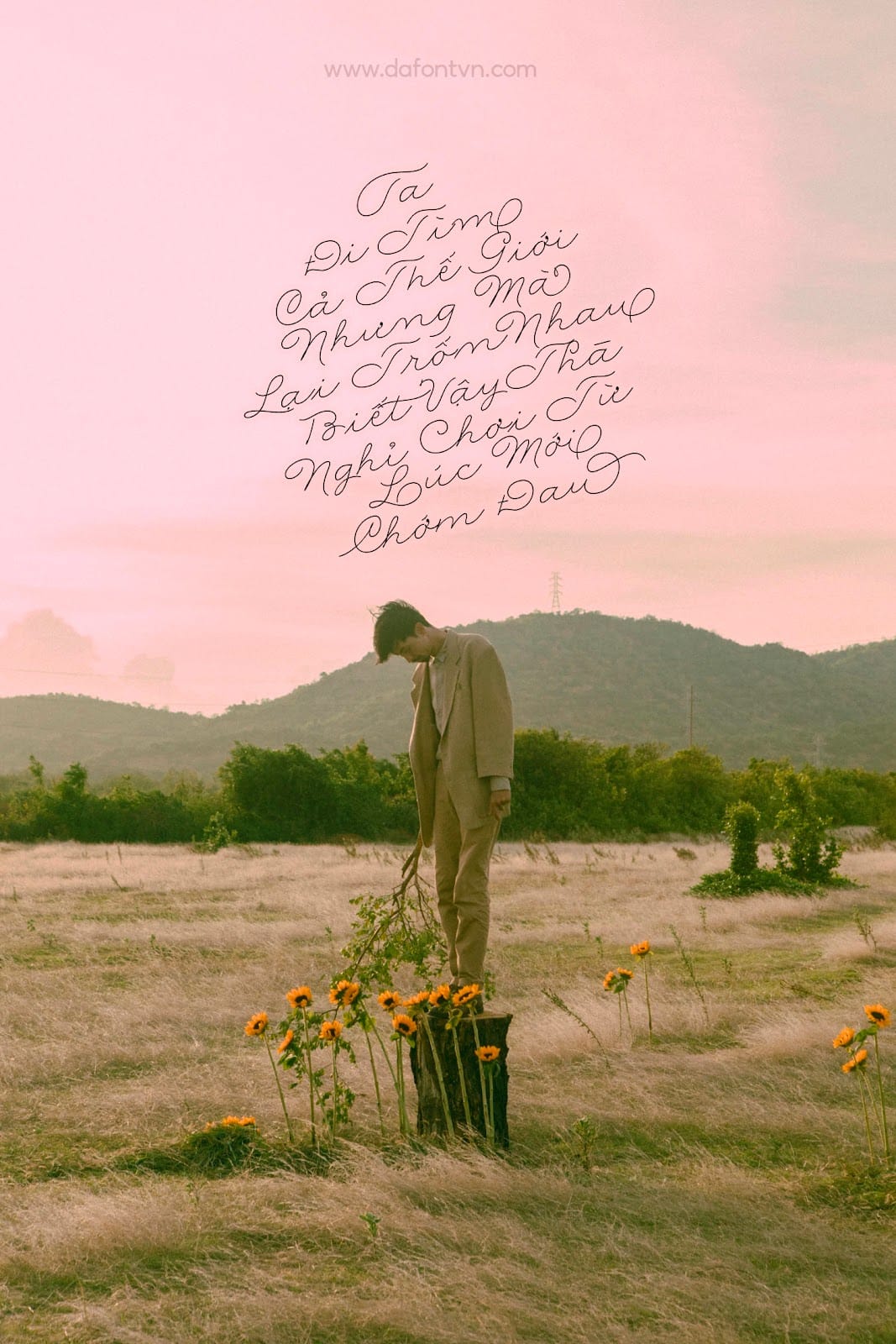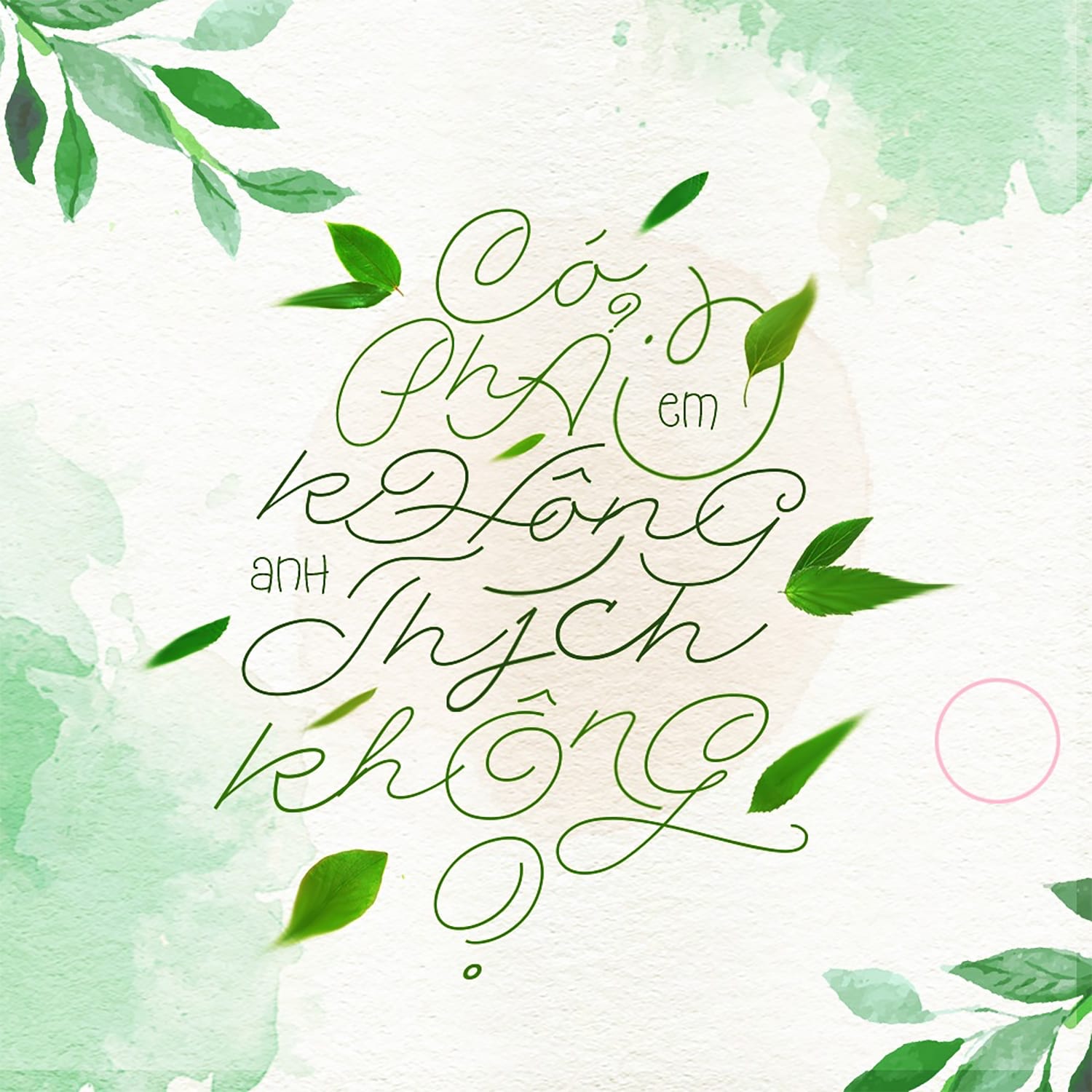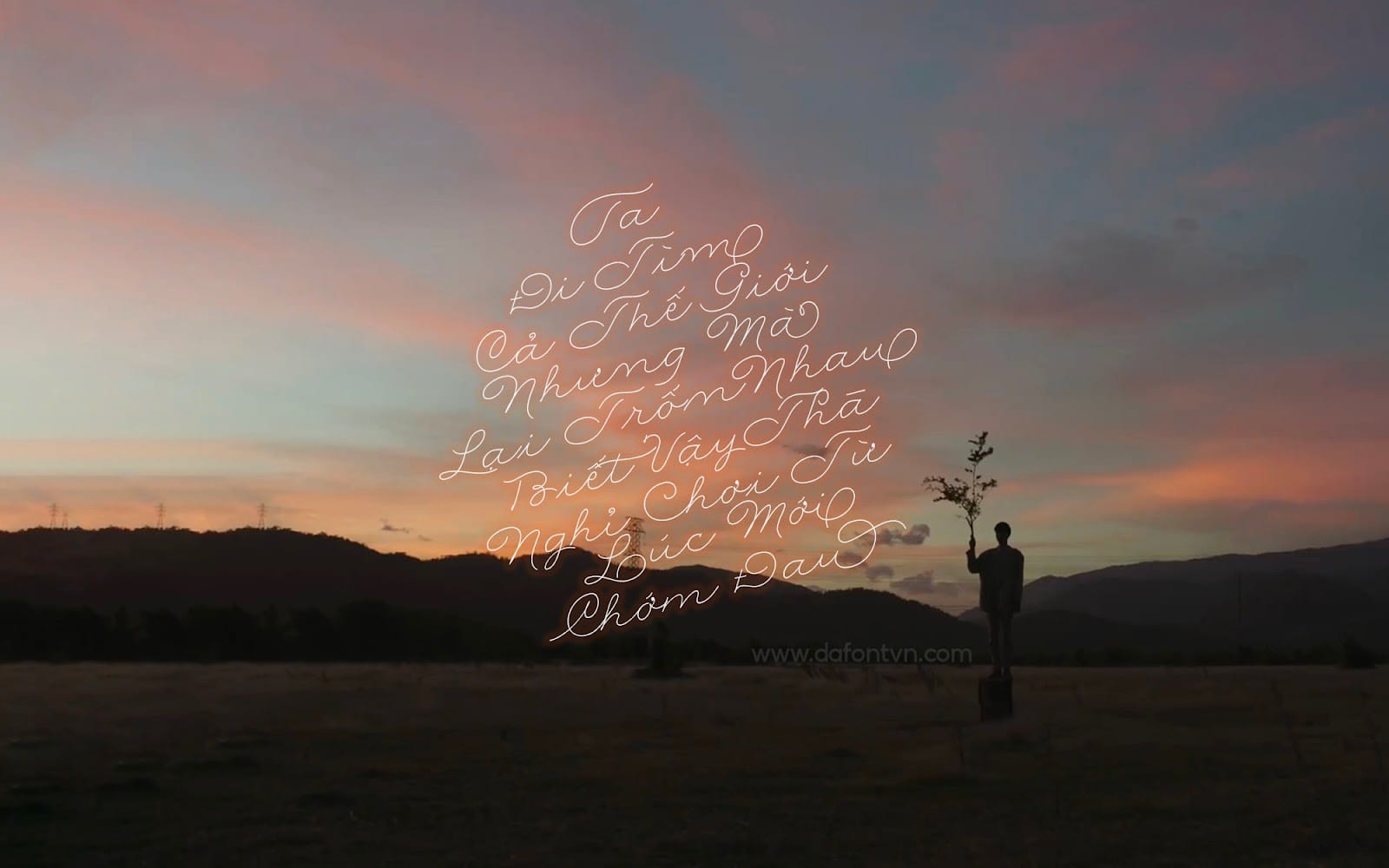
Rolling Pen Font Việt Hóa là một phông chữ viết tay với các nét vẽ được thiết kế tỉ mỉ trong từng chữ mang đến sự hài hòa, ấn tượng và chuyên nghiệp giống như chữ viết tay thật.
Font Rolling Pen Việt Hóa đã được kerning lại, việt hóa đầy đủ và tối ưu hóa trên mọi thiết bị. Ngoài ra phông chữ này còn bao gồm rất nhiềy Glyphs đẹp để bạn có thể ghép và thay thế các ký tự khác nhau.